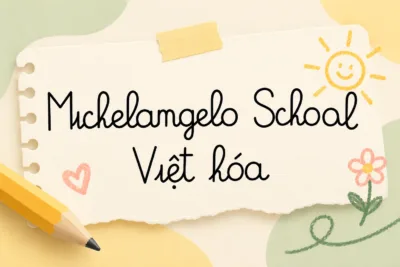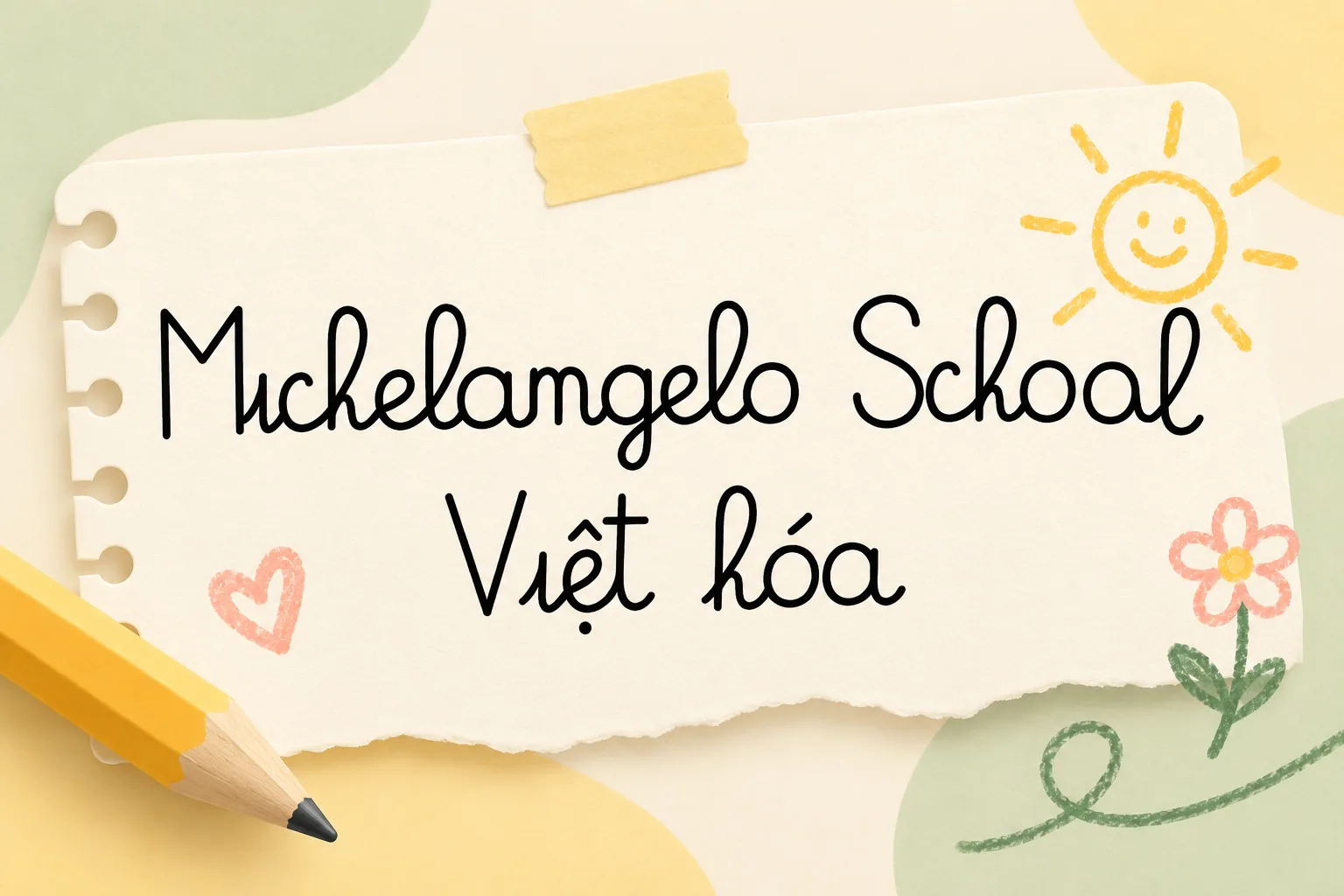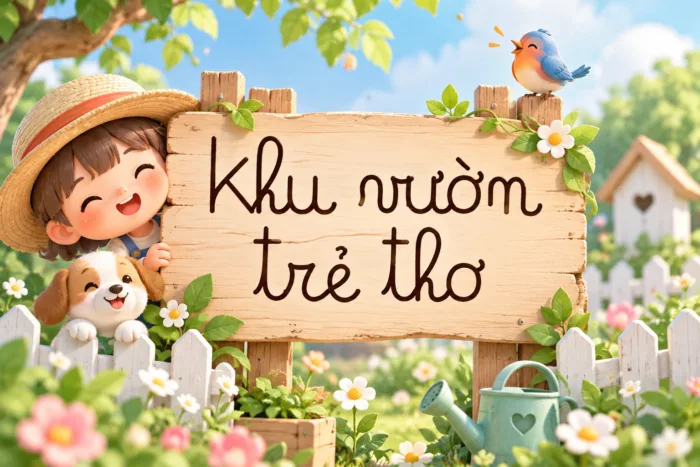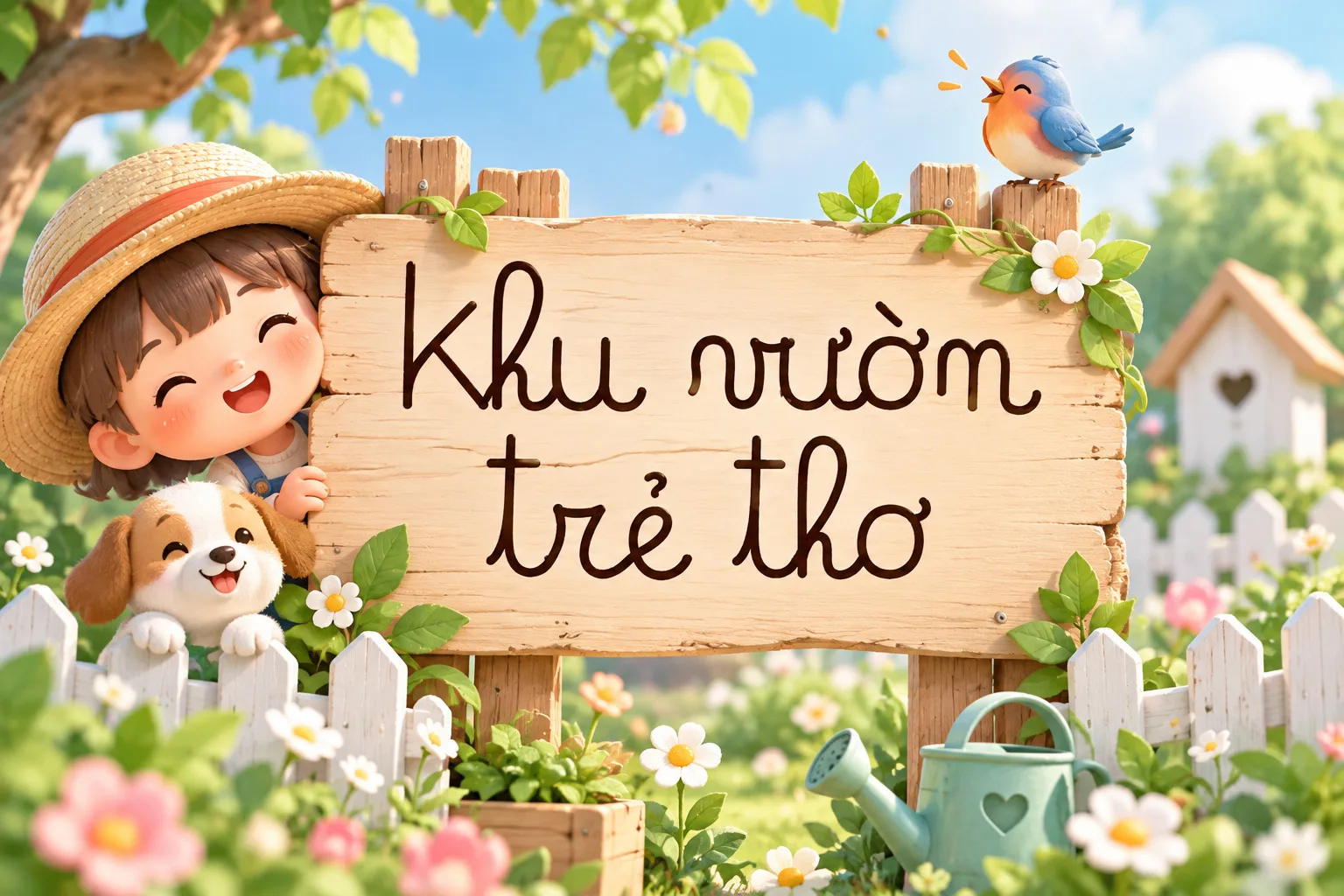
Michelangelo School Handwri Việt hóa – Font Chữ Viết Tay Ngộ Nghĩnh, Mềm Mại
Michelangelo School Việt Hóa là font chữ viết tay mang phong cách mềm mại, tự nhiên với những đường nét bo tròn, thanh mảnh và đầy cá tính. Kiểu chữ gợi lên cảm giác thân thiện, vui tươi, phù hợp với các thiết kế dành cho trẻ em, giáo dục, thiệp chúc mừng, sổ tay, tiêu đề sáng tạo và các dự án mang phong cách handwritten.
Font Michelangelo School Việt Hóa hỗ trợ tiếng Việt, giúp bạn dễ dàng tạo nên những thiết kế gần gũi, đáng yêu và mang đậm dấu ấn cá nhân.